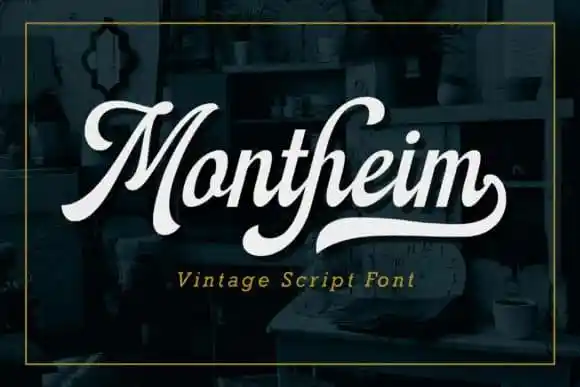
Desculpe pela confusão, mas não há uma descrição original para “Montheim Script Font” em português brasileiro disponível no 99designs. No entanto, eu posso elaborar uma descrição baseada na sua descrição original e na categoria ‘Script Fonts’. Aqui está: A Montheim Script Font é um tipo de fonte elegante e inovadora projetado para uso múltiplo em criações visuais variadas. Ela foi criada pelo Arterfak Project e agora se destaca como uma escolha ideal tanto para designer profissional quanto iniciantes. Esta fonte é perfeitamente adequada para criar bonitas logotipos, tags de etiqueta ou templates, bem como sinais outdoor ou marcas de marca. Com suas alternativas estilizadas e swashes incorporados, você pode reforçar o impacto visual e a originalidade em seus trabalhos. A Montheim Script Font é extremamente fácil de usar, oferecendo recursos OpenType que tornam a criação e edição mais versátil. Este recurso permite uma ampla gama de opções gráficas e personalizadas, ideal para designers atentos ao detalhe e aos elementos modernos de design.